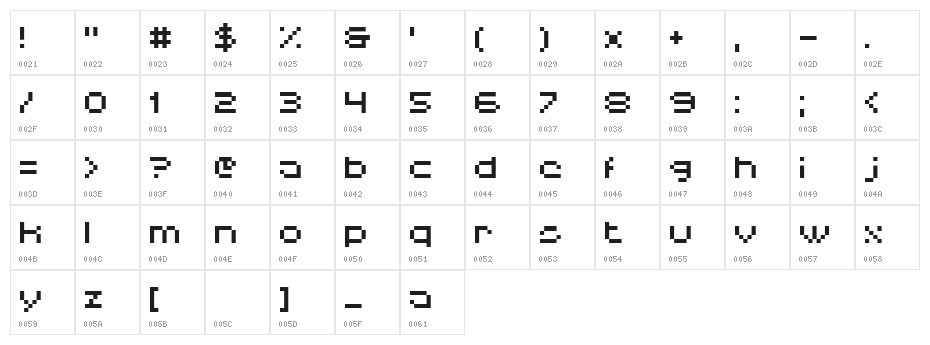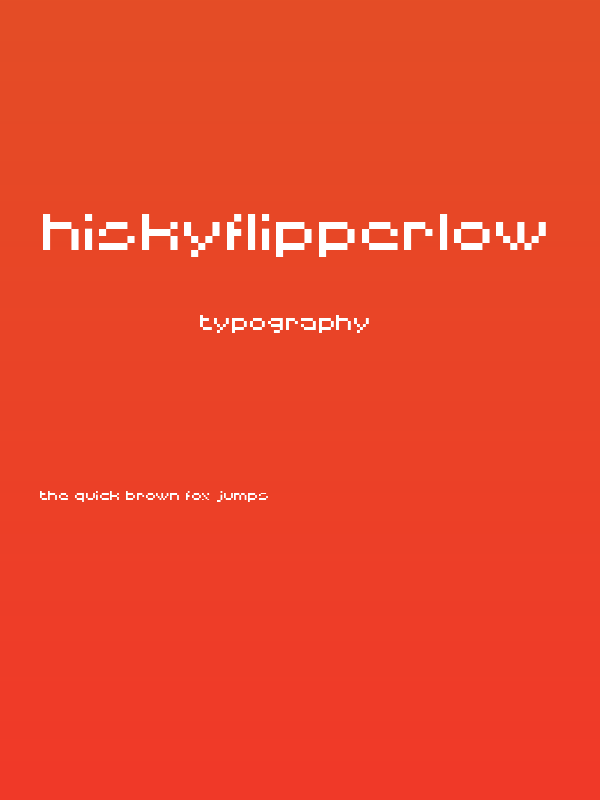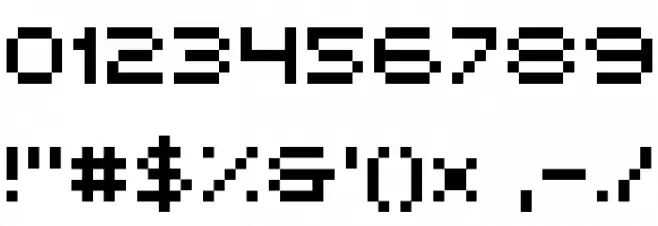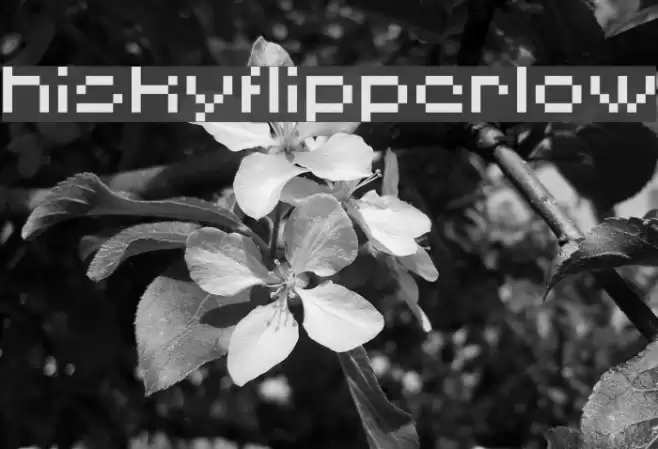
HISKYFLIPPERLOW Font
✎ Pixel
| الاسم | HISKYFLIPPERLOW |
| الفئات | Pixel |
| النمط العام | Vintage |
| حالة الاستخدام | Logos, Headlines, Digital Art |
| مشاريع مقترحة | Perfect for retro video game designs, tech-themed posters, digital art projects, and any creative work that seeks to capture a nostalgic or digital vibe. |